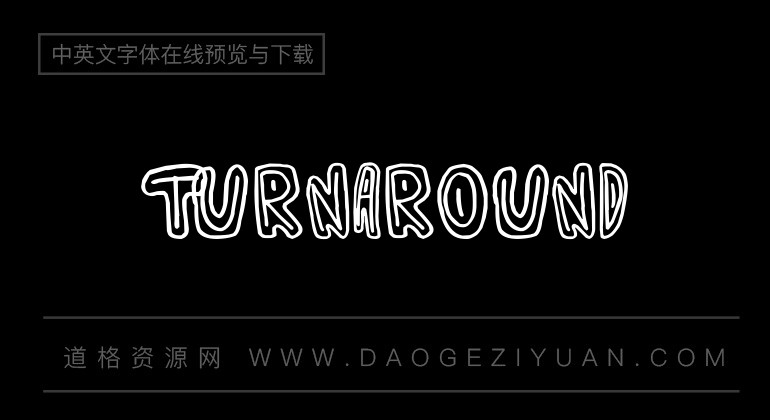
Turnaround
Turnaround 字体是一款精心设计的英文字体,它具有清晰的细节和流畅的曲线,使文字看起来更加精致。它能够在黑色和白色之间轻松切换,使文字更加醒目,更具有吸引力。此外,它的字体大小可以调整,使文字看起来更加清晰,而且它还支持多种语言,使文字更加清晰易读。
Turnaround是一款非常不错的手写艺术字体,具有很好的视觉感,适合于文化类的宣传设计、商业类品牌的广告和产品包装设计以及个性化文字排版等较多场景。